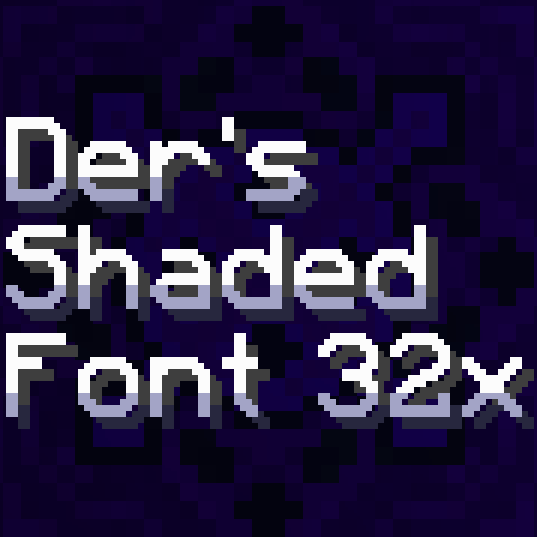
Der's Smooth Shaded Font (Faithful 32x)
Ресурспак, который добавляет плавное цветное затенение к шрифту Faithful 32x в Майнкрафт. Поддерживает более 11 000 символов, множество языков и популярные сервера вроде Hypixel и Wynncraft.
Der's Smooth Shaded Font (Faithful 32x) - это текстурпак для Minecraft, который берет шрифт из Faithful 32x и добавляет к нему аккуратное цветное затенение в нижней части символов. Визуал игры становится свежее и приятнее глазу, особенно если ты часто смотришь на интерфейс, чат или книги. Шрифт перестает быть плоским и получает легкий объем, что делает чтение более комфортным.
Что под капотом
Ресурспак обрабатывает не просто пару десятков букв, а более 11 000 символов. В затенение входят:
В последних версиях добавили еще 8500+ затененных глифов на 37 страницах Unicode. Это значит, что поддерживаются куча языков и редких символов. Плюс исправлены баги ванильного шрифта - например, неправильная ширина у некоторых глифов вроде "▚".
Для кого это
Ресурспак пригодится всем, кто играет с Faithful 32x и хочет, чтобы шрифт выглядел стильно. Особенно полезно на серверах вроде Hypixel (там много своих символов) и Wynncraft (подсветка тултипов). Если ты стримишь или записываешь видео - такой шрифт делает картинку приятнее для зрителей.
Про жирный шрифт: некоторые тонкие символы при выделении жирным могут выглядеть двойными или контурными. Это особенность Minecraft - он просто дублирует символ и сдвигает на два пикселя. Ресурспак тут бессилен, так что лучше не использовать жирный для таких символов.